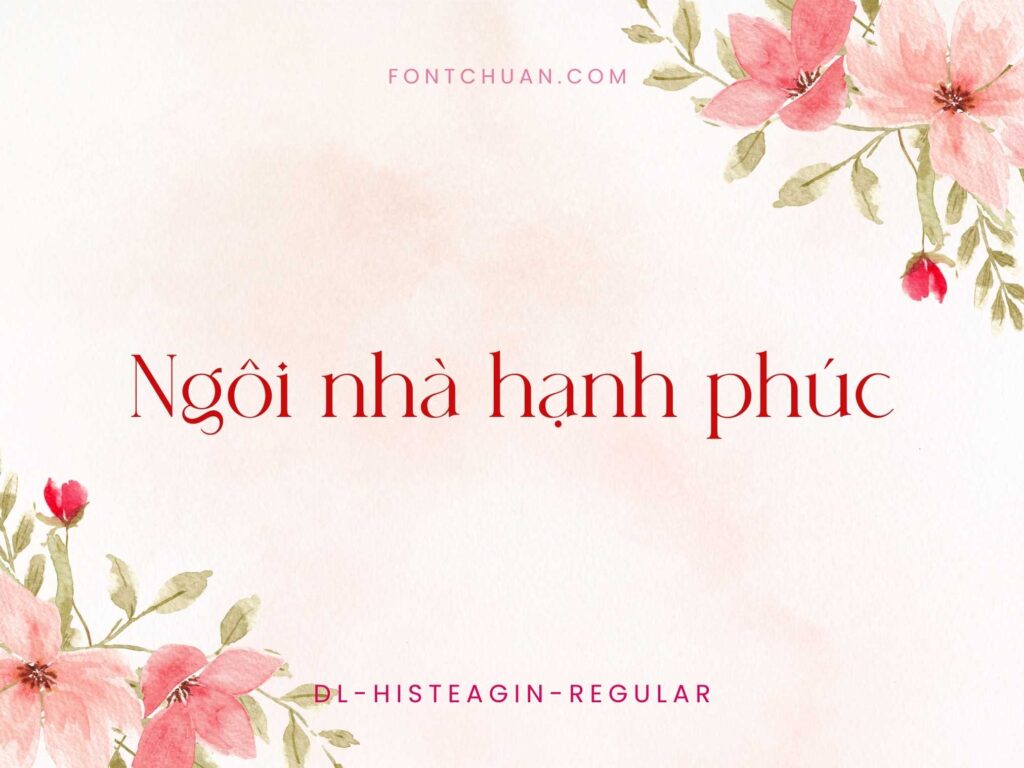
Font DL Histeagin Việt Hóa
Histeagin là một font chữ serif hiện đại, được thiết kế bởi Yahya Qara, mang đến sự kết hợp tinh tế giữa các đường cong mềm mại và cấu trúc chữ thanh lịch. Font này hỗ trợ đa ngôn ngữ, giúp người dùng dễ dàng ứng dụng trong nhiều dự án thiết kế khác nhau. Với sự Việt hóa của Tduy, Histeagin đã được tối ưu hóa để hiển thị đẹp mắt với tiếng Việt. Thành viên của Font Chuẩn đã sưu tầm và chia sẻ font này, đáp ứng nhu cầu đa dạng của cộng đồng thiết kế.
Về đặc điểm thiết kế, Histeagin sở hữu các ký tự với đường nét thanh mảnh, độ tương phản cao giữa các nét đậm và nét mảnh, tạo nên sự cân đối và dễ đọc. Font này bao gồm các tính năng như ligatures và nhiều ký tự thay thế, mang lại sự linh hoạt cho các nhà thiết kế trong việc sáng tạo. Histeagin phù hợp cho các dự án thiết kế như logo, thương hiệu, thiệp mời, bài đăng trên mạng xã hội, quảng cáo và bao bì sản phẩm. Đặc biệt, font này thích hợp cho các ngành nghề như quảng cáo, thiết kế đồ họa, thời trang và truyền thông, nơi cần sự tinh tế và chuyên nghiệp trong trình bày nội dung.